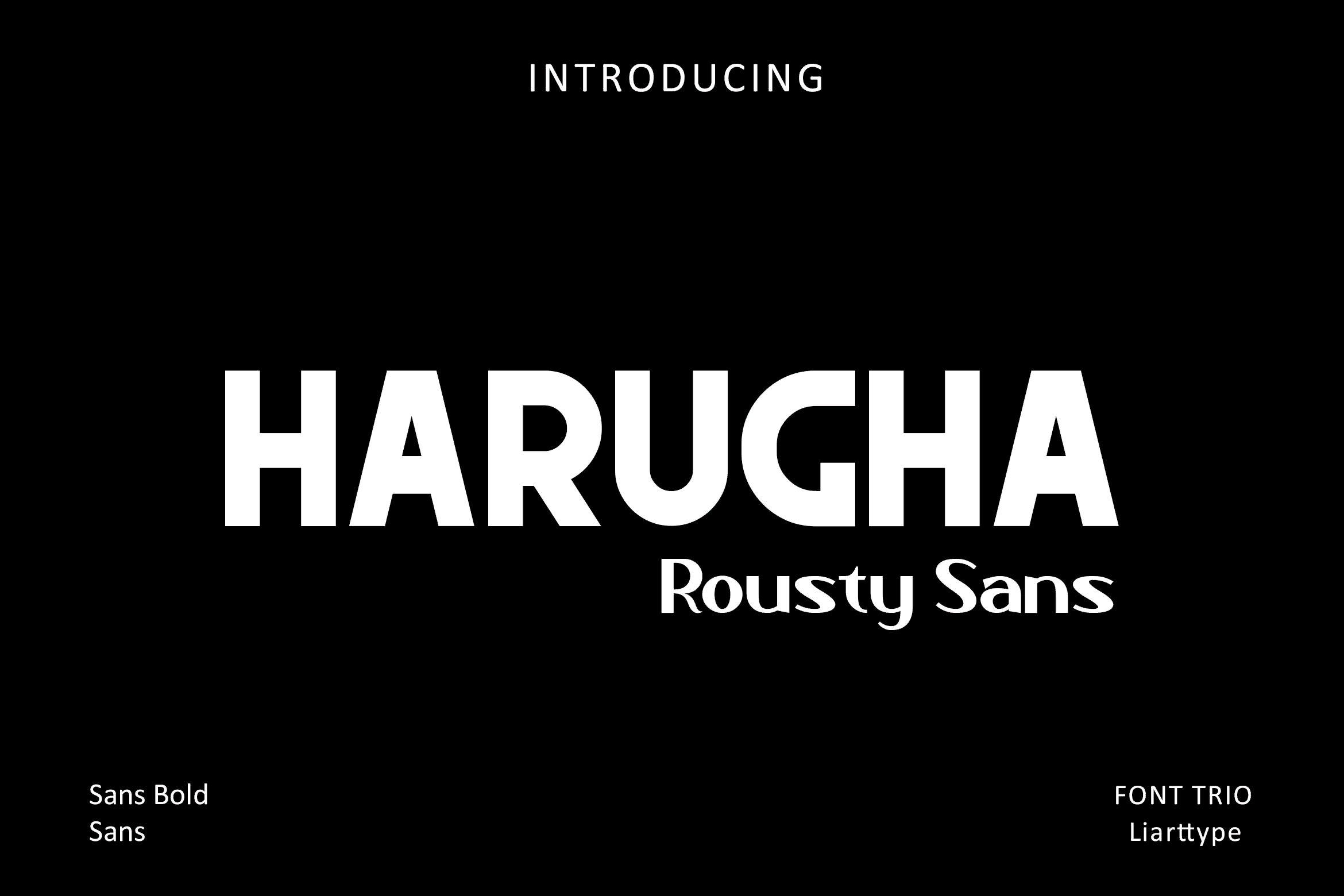
Встречайте наш новый продукт, мы называем его шрифт Harugha Rousty Line.
Шрифт Harugha Rousty Line - это шрифт, сочетающий в себе начертание slab и sans.
который может помочь вам в создании
модных журналов, логотипов, фотографий, целевых страниц, флаеров,